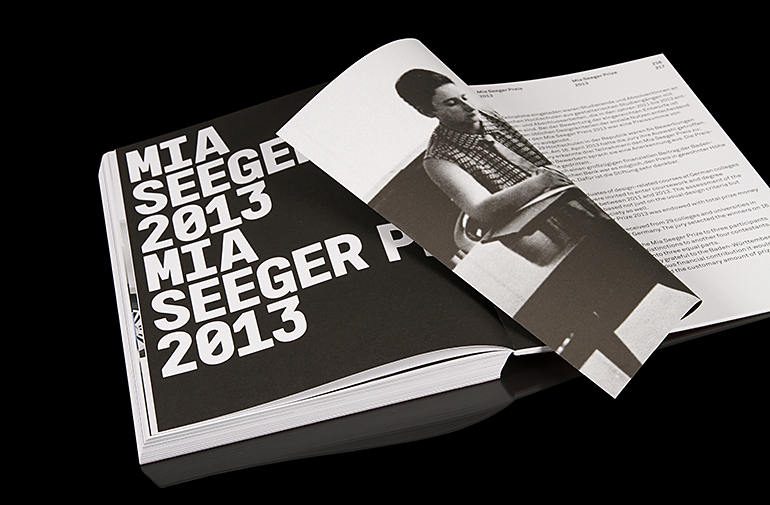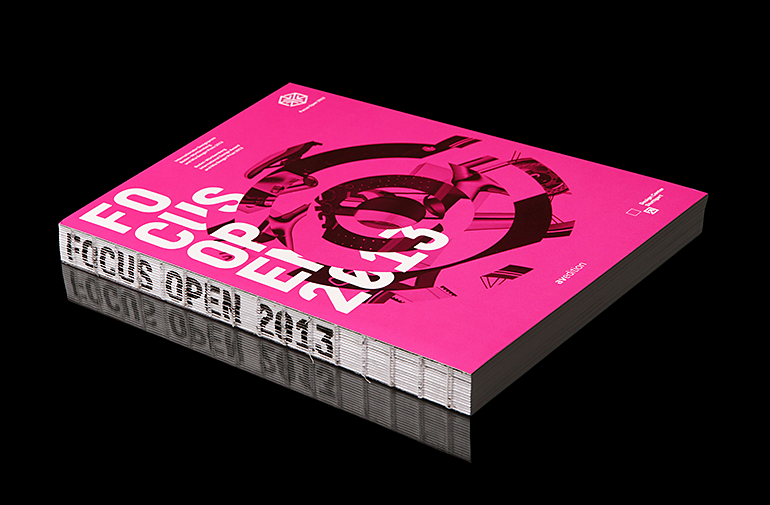
Suche Monospace-Schrift von »Focus Open«
kann mir jemand sagen, welche condensed-anmutende Monospace hier für diese »Focus Open«-Kataloge verwendet wird?
Stapelberg und Fritz scheinen die Typo öfter zu verwenden. Hier ein anderes Projekt:
"Protokoll 02" von Alex W. Dujet.
So ganz monospace ist die nicht: z. B. sind A und W breiter als die anderen. Dafür scheint sie Kerning zu unterstützen.
Vielen Dank. Scheint aber nicht offiziell verfügbar zu sein. Zu mindest finde ich über Google keine Bezugsquelle. :-? Schade.